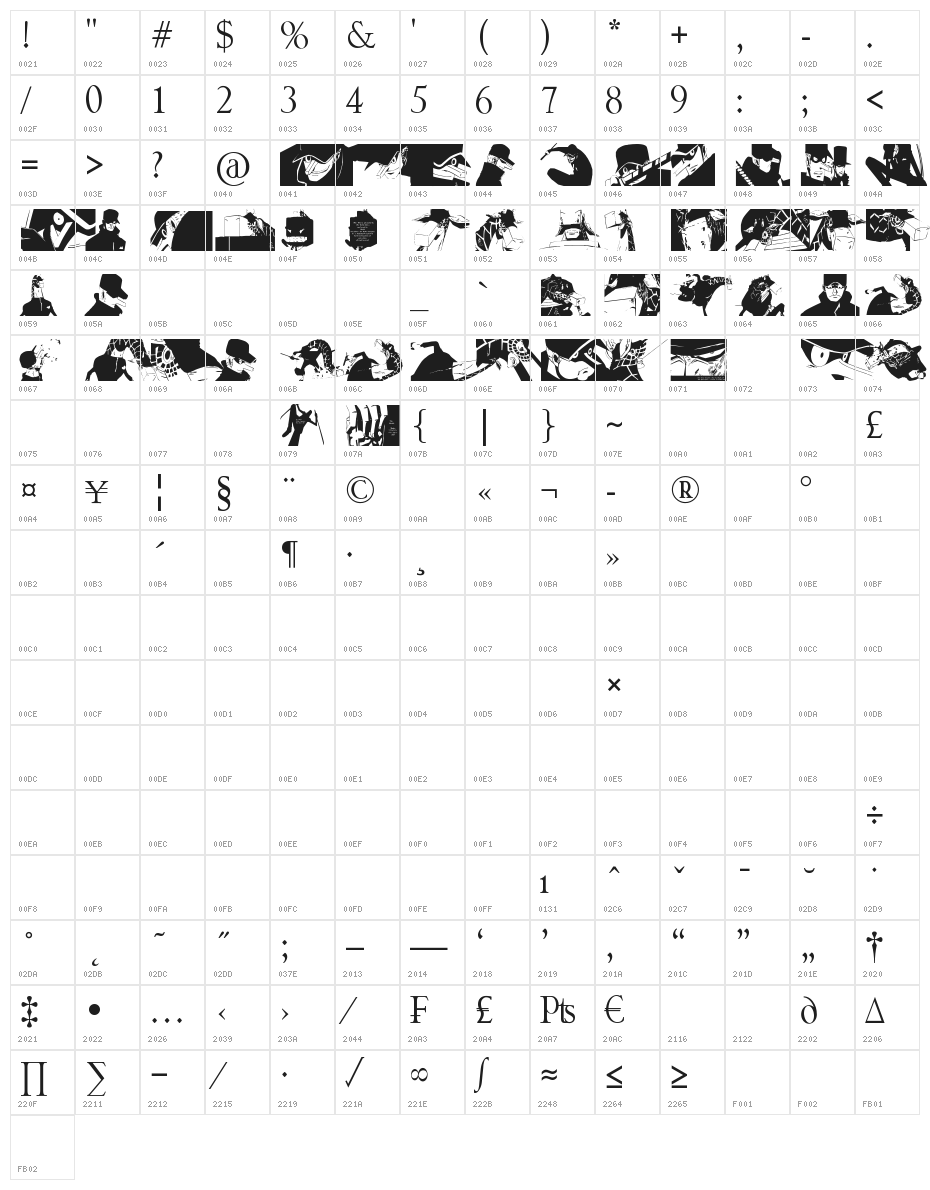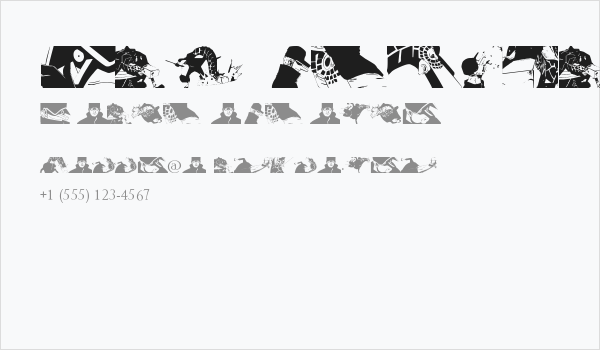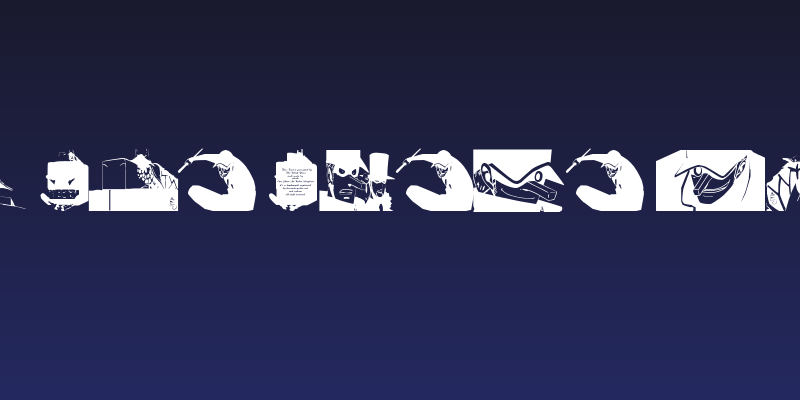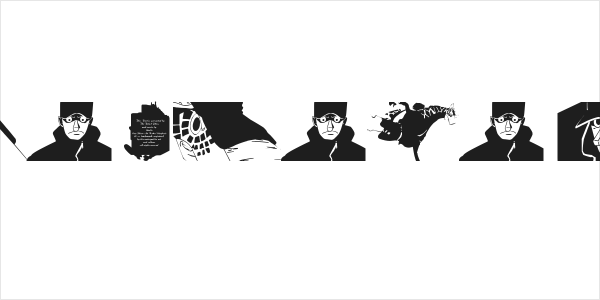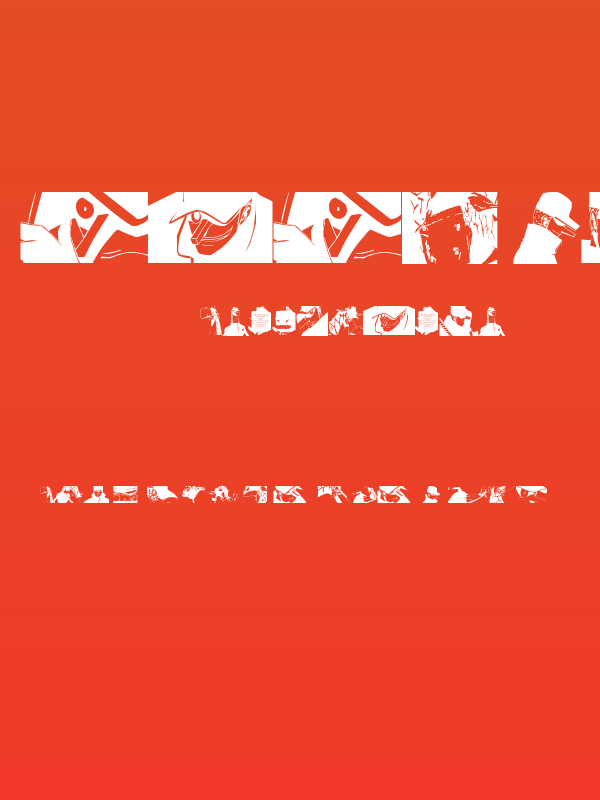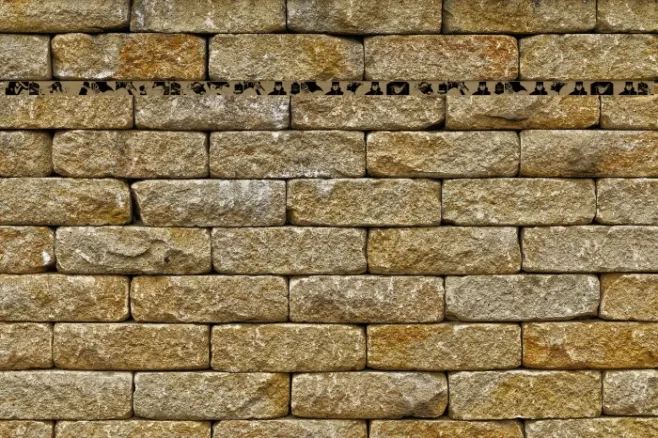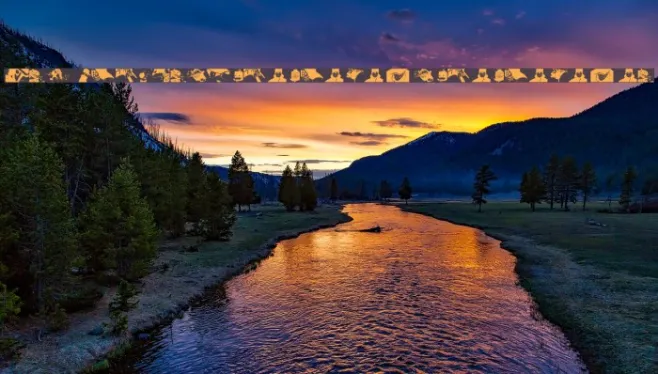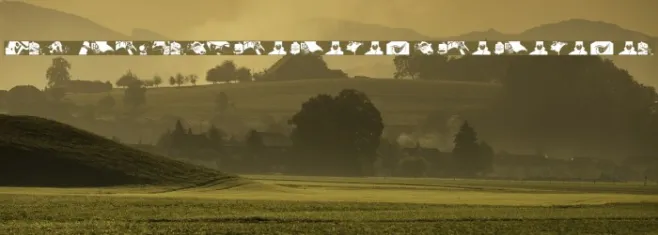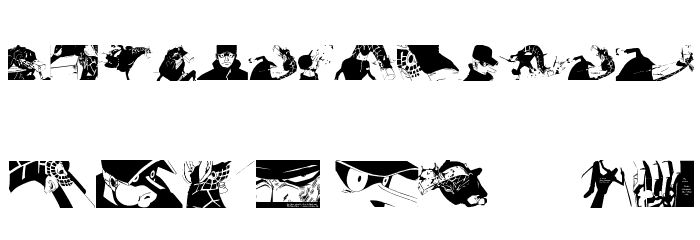
Kaku Dingbats One Piece Art One Piece Area Font
| Cas d'utilisation | Logos, Posters, Artistic Projects |
| Projets proposés | Ideal for artistic posters, creative branding, unique invitations, and any project that benefits from a blend of art and typography. |